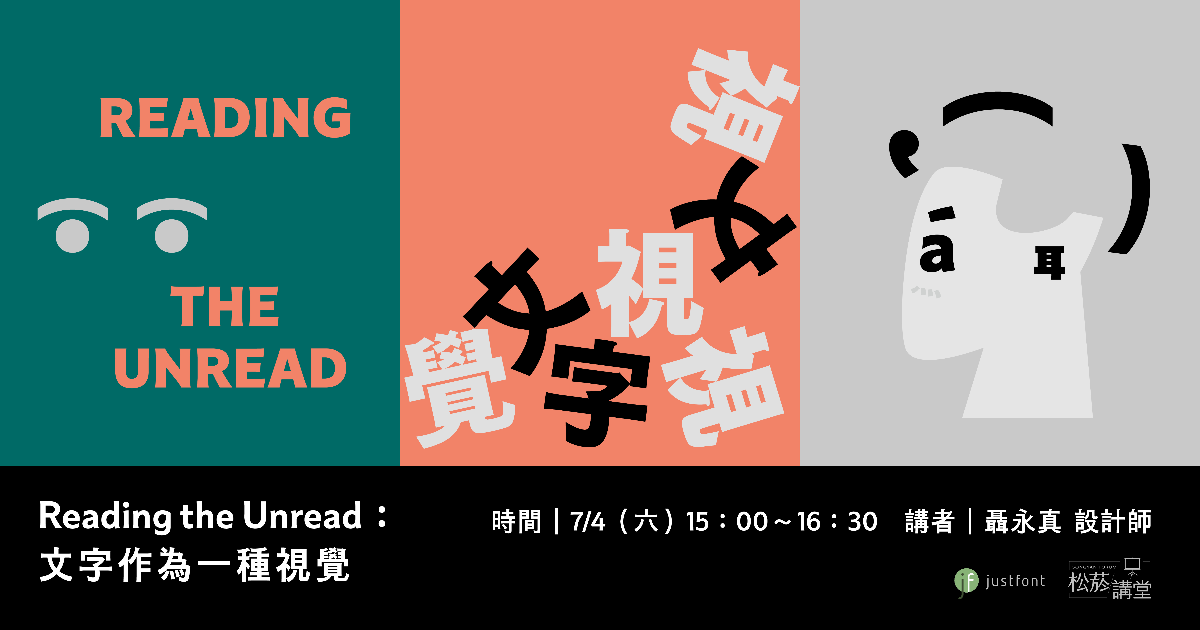
本場活動為造字鼓勵元 S10 概念獎評審特別講座。本屆概念獎評審邀請設計師聶永真,從多年的設計經驗,提供來自業界的真實觀點。
在視覺傳達設計的語境裡,文字從來不只是傳遞資訊的載體。這場講座將透過永真急制Workshop過往的平面設計作品,聊聊隱形於每個專案背後的字體選擇決策;以及文字作為一種視覺,在版面中所掌控的「權威」與「氣質」—— 文字何時該退居幕後,何時又該成為主角。
關於講者
聶永真為瑞士國際平面設計聯盟(AGI)首位台灣會員,其工作室團隊「永真急制Workshop」作品繁不及載,跨及唱片、文化、劇場與品牌等領域;擅於從創作源頭涉入更多詮釋和引導,熟練而從容地駕馭畫面、符號及素材,開拓了另一種觀看平面視覺與理解的角度。
講者:聶永真(設計師)